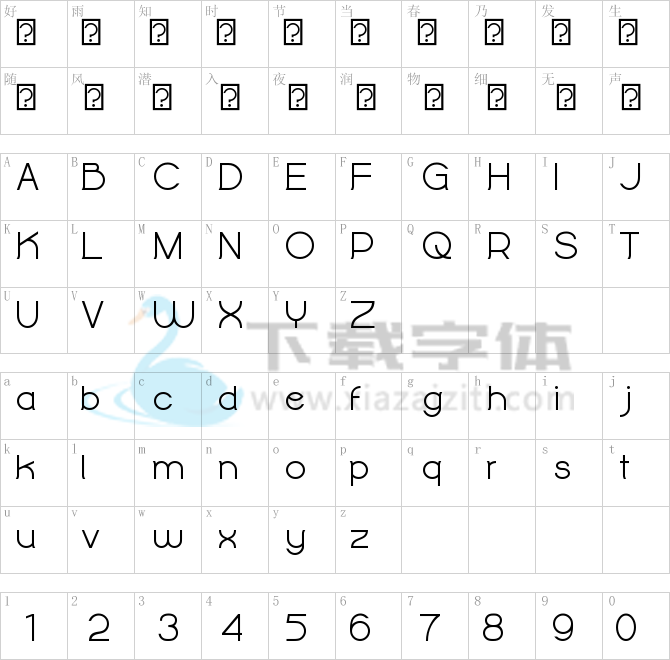
Alighty Nesia Bold.ttf字体下载,这款字体结构工整、笔画清晰,兼顾美观与易读性,适用于标题、正文、海报、包装、LOGO 等多种场景。字形优雅稳定,风格百搭耐看,适配日常排版与创意设计,让文字呈现更舒适、更具质感。Alighty Nesia Bold.ttf字体下载一笔一画,皆是细节,以均衡的比例、流畅的线条打造舒适视觉体验,字形端正大气,风格简约现代。无论是商业设计、品牌宣传还是日常排版,都能轻松驾驭,让文字更有格调与力量。Alighty Nesia Bold.ttf字体下载字体下载。